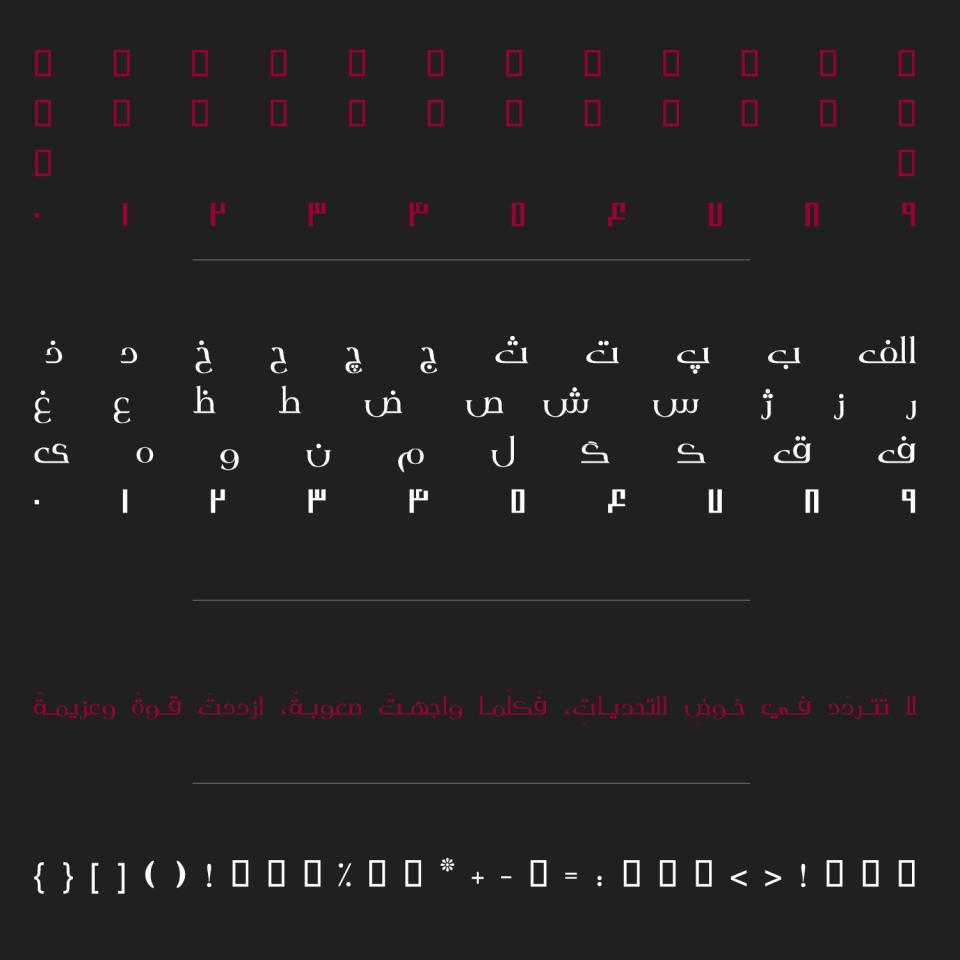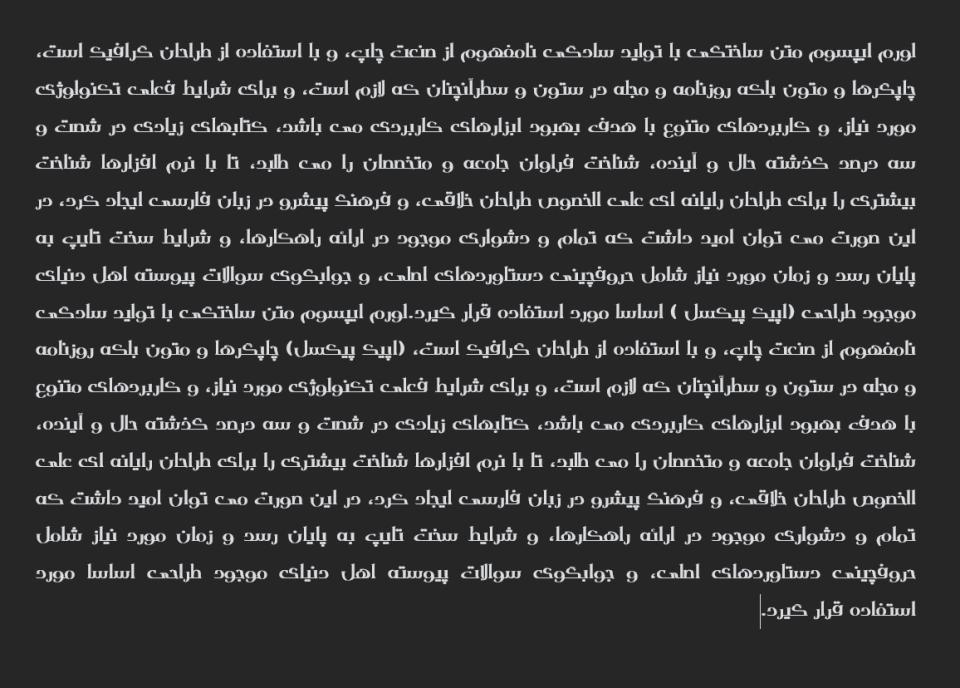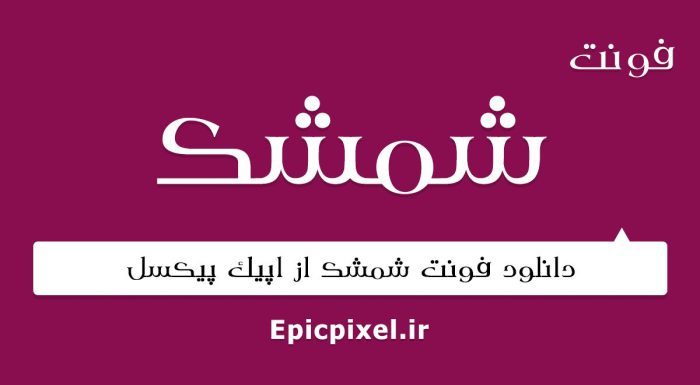
2 فونت شمشک فارسی Shemshak
فونت شمشک فارسی، با طراحی خاص و منحصربه فردش، می تواند جلوه ای متفاوت به نوشته های شما ببخشد. این فونت با نقطه های گرد و خطوط باریک، ترکیبی دلنشین از ظرافت و خوانایی را ارائه می دهد. تصور کنید متنی را با این فونت می خوانید؛ نرمیِ خطوط، چشم را نوازش می دهد و در عین حال، به دلیل طراحی دقیق، خواندن آن بسیار آسان است. این ویژگی به خصوص در متن های طولانی یا صفحاتی با طراحی شلوغ، اهمیت خود را نشان می دهد و از خستگی چشم جلوگیری می کند.
یکی از ویژگی های برجسته شمشک، هماهنگی آن با انواع طراحی هاست. چه یک پوستر تبلیغاتی طراحی کنید، چه یک متن رسمی، شمشک می تواند به خوبی با محتوای شما هماهنگ شود. این فونت، نه خیلی رسمی و خشک است و نه خیلی فانتزی و غیرجدی؛ بلکه تعادلی مناسب بین این دو حالت دارد. این یعنی شما می توانید در موقعیت های مختلف، از آن بهره ببرید و نگران ناهماهنگی آن با طرح خود نباشید.
البته شمشک، مانند هر فونت دیگری، محدودیت هایی نیز دارد. به دلیل ظرافت خطوط، شاید در اندازه های بسیار کوچک، خوانایی آن کمی کاهش یابد. بنابراین، توصیه می شود در طراحی هایی که نیاز به نمایش متن در ابعاد کوچک دارند، از فونت های دیگری که ضخامت بیشتری دارند استفاده کنید. با این حال، در بیشتر موارد، شمشک انتخابی عالی برای نوشته های شما خواهد بود. رایگان بودن این فونت هم مزیتی است که نمی توان از آن چشم پوشی کرد. شما می توانید بدون هیچ هزینه ای، از این فونت زیبا و کاربردی در پروژه های خود استفاده کنید و به نوشته های خود، جلوه ای خاص ببخشید.